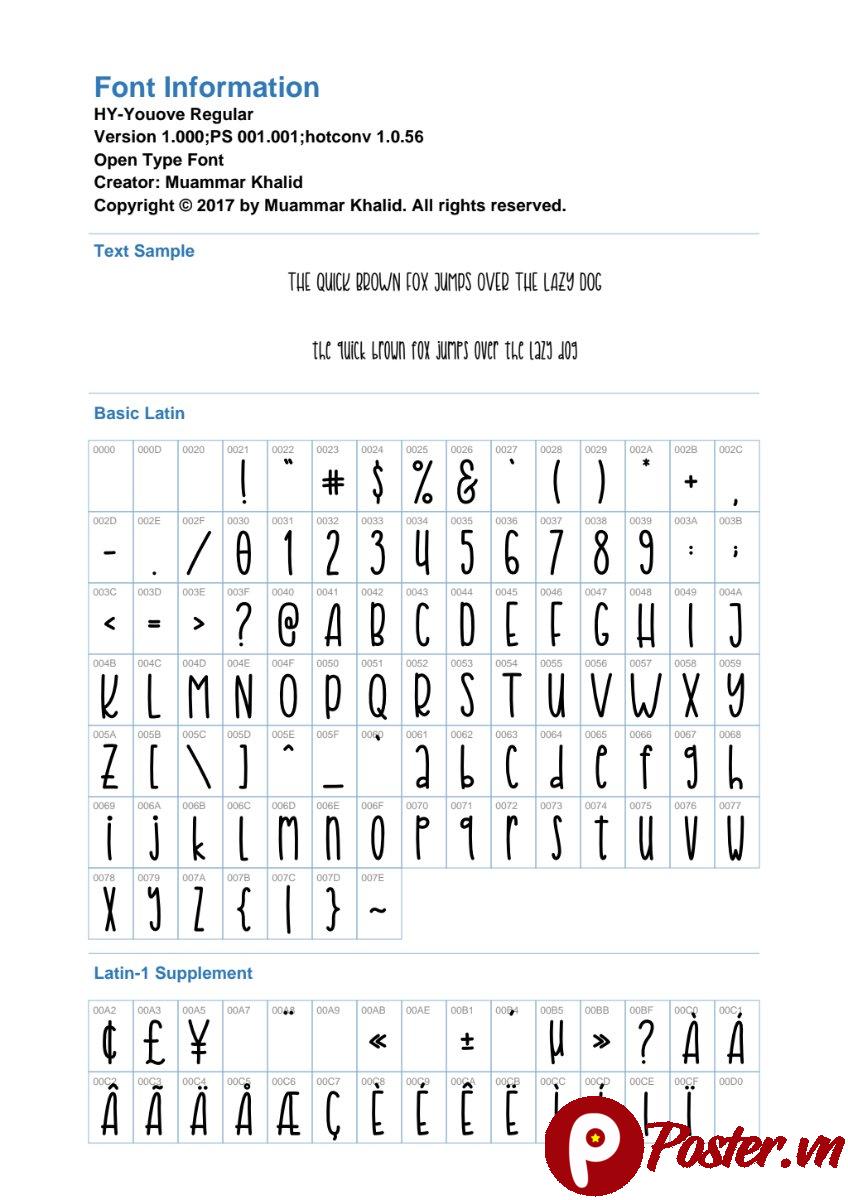
Font Chữ HY-Youove Độc Đáo
Font Chữ HY-Youove Độc Đáo. Khám phá font chữ HY-Youove độc đáo, mang phong cách viết tay tự nhiên và cá tính. Hoàn hảo cho thiết kế sáng tạo, tiêu đề ấn tượng và các dự án nghệ thuật. Tải ngay tại Poster.vn để tạo điểm nhấn cho tác phẩm của bạn.
Trong thế giới thiết kế đồ họa đầy sáng tạo, việc lựa chọn một font chữ phù hợp có thể tạo nên sự khác biệt lớn cho tác phẩm của bạn. Và hôm nay, Poster.vn hân hạnh giới thiệu đến bạn một tài nguyên font chữ vô cùng độc đáo và ấn tượng: Font HY-Youove. Với phong cách viết tay tự nhiên, cá tính và đầy ngẫu hứng, HY-Youove chắc chắn sẽ là lựa chọn lý tưởng để thổi hồn vào các dự án thiết kế của bạn.
Font HY-Youove: Nét Chữ Viết Tay Đầy Cá Tính
Font HY-Youove được thiết kế với cảm hứng từ những nét chữ viết tay phóng khoáng, mang đến một vẻ đẹp gần gũi nhưng không kém phần nghệ thuật. Mỗi ký tự trong HY-Youove đều thể hiện sự tự do, không gò bó, tạo nên một tổng thể hài hòa và thu hút. Đây không chỉ là một font chữ, mà còn là một công cụ để bạn thể hiện cá tính và sự sáng tạo không giới hạn của mình.
Đặc Điểm Nổi Bật Của Font HY-Youove
• Phong cách viết tay độc đáo: HY-Youove nổi bật với những nét chữ mềm mại, uyển chuyển như được viết bằng tay, tạo cảm giác chân thực và gần gũi.
• Cá tính mạnh mẽ: Dù mang phong cách viết tay, font chữ này vẫn toát lên sự mạnh mẽ, hiện đại, phù hợp với nhiều loại hình thiết kế khác nhau.
• Đa dạng ký tự: HY-Youove hỗ trợ đầy đủ các ký tự Latin cơ bản, số, dấu câu và một số ký tự Latin-1 Supplement, giúp bạn linh hoạt trong việc sử dụng.
• Dễ đọc và dễ ứng dụng: Mặc dù có phong cách riêng, các ký tự của HY-Youove vẫn đảm bảo độ dễ đọc, giúp thông điệp của bạn được truyền tải rõ ràng.
Ứng Dụng Sáng Tạo Với Font HY-Youove
Với những đặc điểm nổi bật, Font HY-Youove có thể được ứng dụng trong rất nhiều lĩnh vực thiết kế khác nhau, giúp bạn tạo ra những sản phẩm độc đáo và thu hút:
Thiết Kế Tiêu Đề và Logo
Font HY-Youove là lựa chọn tuyệt vời cho các tiêu đề bài viết, poster, banner hoặc logo thương hiệu muốn thể hiện sự sáng tạo, trẻ trung và cá tính. Những nét chữ viết tay sẽ giúp tiêu đề của bạn nổi bật và dễ gây ấn tượng.
Thiết Kế Bao Bì Sản Phẩm
Đối với các sản phẩm thủ công, sản phẩm dành cho giới trẻ hoặc các thương hiệu muốn tạo dựng hình ảnh gần gũi, thân thiện, HY-Youove sẽ là một điểm nhấn độc đáo trên bao bì, giúp sản phẩm của bạn trở nên khác biệt.
Thiết Kế Thiệp Mời, Thư Mời
Khi cần tạo ra những tấm thiệp mời sinh nhật, thiệp cưới hoặc thư mời sự kiện với phong cách ấm áp, cá nhân hóa, HY-Youove sẽ mang đến một vẻ đẹp tinh tế và độc đáo, thể hiện sự chân thành của người gửi.
Thiết Kế Đồ Họa Mạng Xã Hội
Trong thời đại kỹ thuật số, việc tạo ra nội dung hấp dẫn trên mạng xã hội là vô cùng quan trọng. HY-Youove có thể giúp bạn thiết kế những hình ảnh, quote, hoặc story Instagram, Facebook với phong cách riêng biệt, thu hút sự chú ý của người xem.
Thiết Kế Sách, Tạp Chí và Trang Web
Đối với các ấn phẩm muốn có một chút phá cách, nghệ thuật, HY-Youove có thể được sử dụng cho các tiêu đề chương, trích dẫn hoặc các phần đặc biệt, tạo điểm nhấn thị giác thú vị. Trên website, font chữ này cũng có thể dùng cho các tiêu đề blog hoặc phần giới thiệu để tăng tính thẩm mỹ.